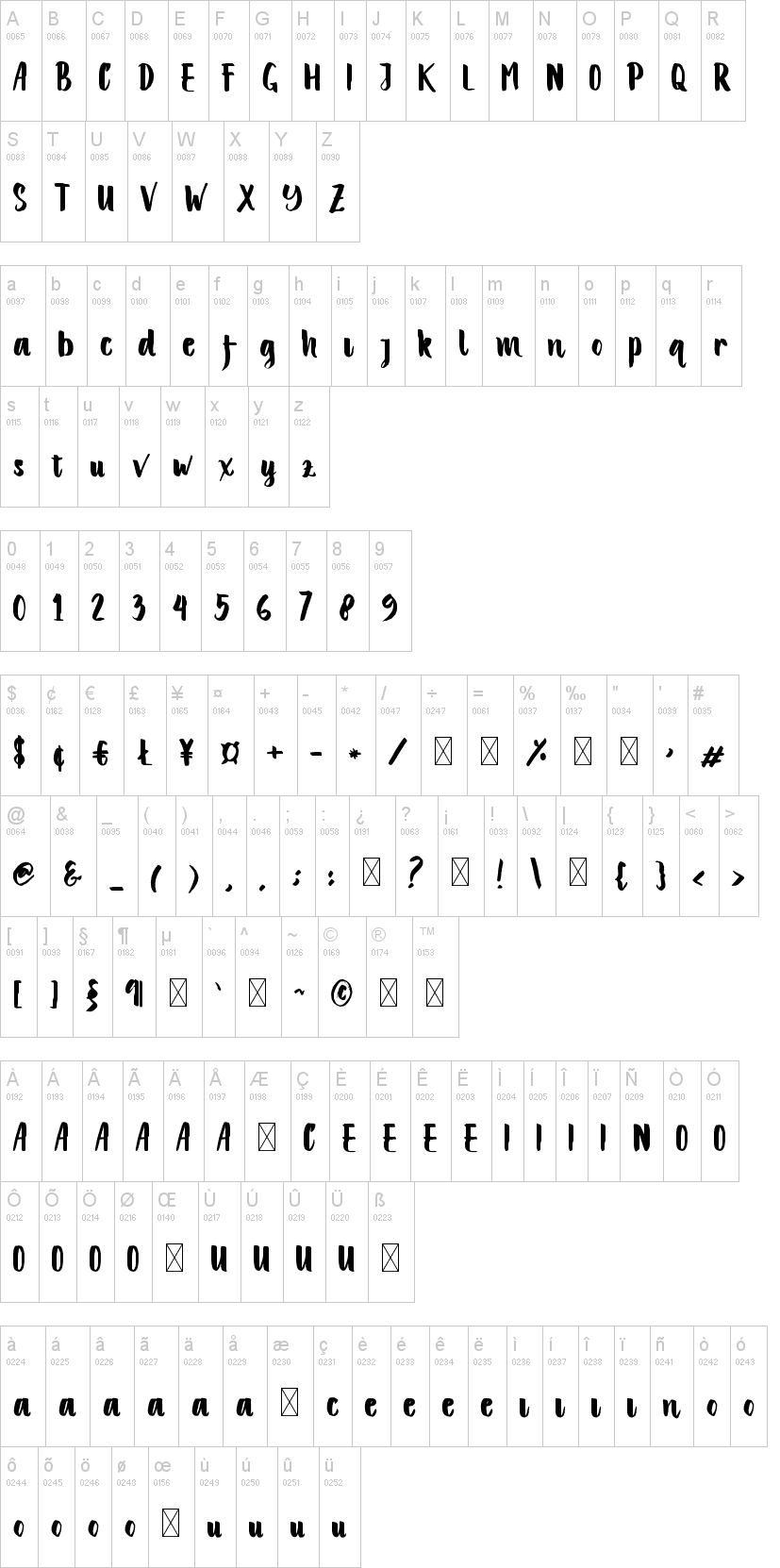
Chocolatos
Chocolatos 是由设计师 Alexey Frolov 创作的一款温暖的旋律字体,它具有完美的曲线和细节,可以给你的设计带来温暖的感觉。Chocolatos 的字体特点是它的弧度更加柔和,字母之间的空隙更大,字体的线条也更加细腻。它的灵感来自于古老的拉丁文和英文字母,让人感受到它的古典气息。同时,Chocolatos 字体可以让你的设计更加有个性,更加有趣和有趣,也可以让你的设计更加生动。
Chocolatos是一款非常不错的手写艺术字体,具有很好的视觉感,适合于文化类的宣传设计、商业类品牌的广告和产品包装设计以及个性化文字排版等较多场景。
Chocolatos字符映射图